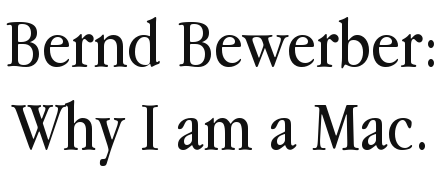
Schrift aus Logo von OTHER SIDE gesucht!
Weiß vieleicht jemand was für eine Schrift das Other Side Logo hat?
Das währe sehr hilfreich, würde diese gerne in meine Bewerbung mit einbringen.
ich würde sagen, der Schriftzug ist handgezeichnet. :-) Aber sag mal, eine Frage aus reiner Neugier: In was für einer Art von Bewerbung willst Du eine solche Schrift einsetzen?
Echt? Ich hätte bei den unausgewogenen Buchstaben nicht an einen Standardfont gedacht – und mit unausgewogen meine ich jetzt nicht in erster Linie die Verzerrungen … ;-) Aber vielleicht bin ich da auch einem Irrglauben aufgesessen, weil mir persönlich das Scribbeln solcher Buchstaben schneller und leichter erscheint als das Herumzerren.
Die haben hier bei un in Dormagen einen Laden auf gemacht & ich wolte mich dort bewerben. Dachte es sieht gut aus wenn ich auf meinem Deckblatt Bewerbung in deren Schriftart schreibe.
Da die Tätowieren ist das gar nicht soooo abwägig mit dem selbst gemalt.
Aber ich weiß halt auch was mit Grafik Programmen so alles möglich ist.
es kommt natürlich immer auf die Firma an – und ein Tattoo-Studio mag das lockerer sehen – aber den meisten Unternehmen würde es eher gegen den Strich gehen, wenn man ihre Logoschrift zweckentfremdet.
den meisten Unternehmen würde es eher gegen den Strich gehen, wenn man ihre Logoschrift zweckentfremdet.
Mit drängt sich hier die Frage auf, wo eine (als solche empfundene) Zweckentfremdung beginnen würde. Sind die meisten Firmen nicht sogar sehr daran interessiert, dass sich ihre Mitarbeiter – und somit wohl auch Bewerber – mit dem Unternehmen identifizieren? Wie kann ein Bewerber das auf den ersten Blick besser vermitteln als dadurch, dass er schon als Bewerber dem CD des hofierten Arbeitgebers eine (maßvolle) Referenz erweist? Ich stelle mir gerade vor, ich hätte für Apple Bewerbungen für Praktika, Lehrstellen und ähnliche Einstiegsjobs sichten müssen.¹ Und zwischen 100.000 Deckblättern, auf denen »Bewerbung« in TNR oder sonst einer Systemschrift prangte, wäre dann dieses hier gewesen:
Was wäre wohl wahrscheinlicher gewesen: dass Bernds Bewerbung aussortiert worden wäre oder dass er im Gegenteil in die engere Auswahl gelangt wäre?
Natürlich gibt es auch hier wie immer Grenzen. So dürfte eine Bewerberin nicht den Eindruck erwecken, sie repräsentiere bereits die Firma oder spreche für sie. Ist die Logoschrift nicht legal zu bekommen, ist sicher auch Vorsicht geboten. Und dann gibt es sicher auch Unternehmen, bei denen jeder unkonventionelle Touch verkehrt wäre und nur möglichst staubtrocken die richtige Strategie ist. Aber sonst? Bei Jobs, in denen Männer nie Schlips tragen würden? Oder gar einer Tätowierbude?
1. zu einer Zeit, in der die Apple Garamond dort noch angesagt war